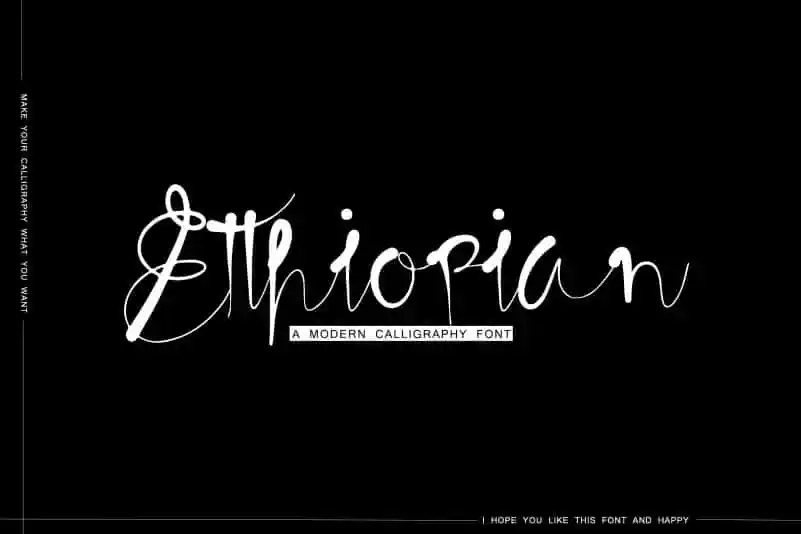
Etthiopian Calligraphy Font – Download Grátis
Na categoria de fonts de calligrafia, apresentamos a Etthiopian Calligraphy Font, uma escolha moderna e minimalista que destaca sua elegância através de linhas limpas e formas geométricas. Este tipo de fonte é ideal para designers buscando um equilíbrio entre simplicidade e sofisticação, perfeito para criar texturas agradáveis sem comprometer o aspecto minimalista. Linyeng_Studio criou esta fonte, trazendo uma nova perspectiva à chamigrafia tradicional. Compostas por linhas retas e formas geométricas modernas, as letras de Etthiopian Calligraphy Font podem ser usadas em diversas aplicações de design, desde o layout de websites até a criação de capas para livros. É uma fonte que combina clareza com um toque elegante, fazendo-a perfeita para qualquer projeto buscando um equilíbrio entre simplicidade e sofisticação.
Designer: Linyeng_Studio